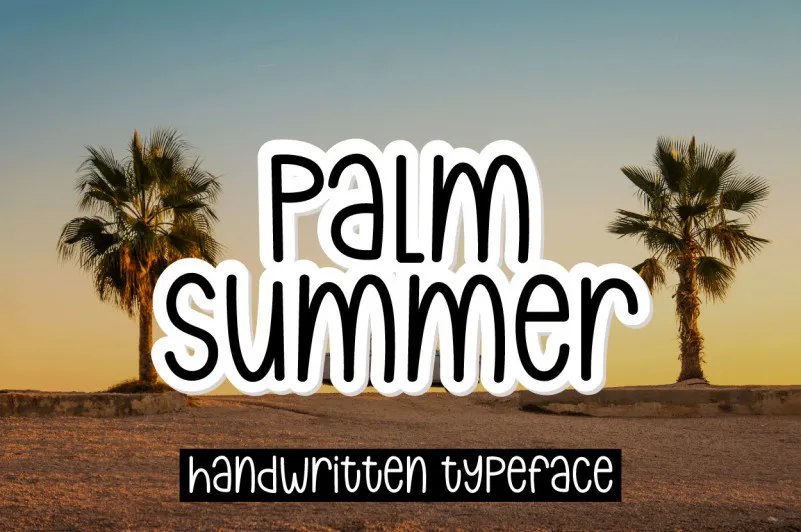
Palm Summer Font – Fonte Grátis
Palm Summer Font
A ‘Palm Summer’ é uma elegante fonte de linhas retas perfeita para qualquer projeto que precise de um visual limpo e moderno. Embora leve e versátil, esta font traz consigo uma rara sensação de verão tropical em cada letra, tornando-a não apenas útil, mas também deliciosamente envolvente. Seja para aplicativos móveis, design editorial ou qualquer projeto digital que você possa imaginar, a ‘Palm Summer’ é o tipo perfeito para destacar seu trabalho de forma única e inspiradora. Ela foi criada pelo talentoso designer sugiharto1790, oferecendo uma combinação perfeita de beleza e simplicidade ideal para qualquer projeto visual. Instale-a hoje e experimente o encanto da Palm Summer no conforto do seu escritório ou mobile device!